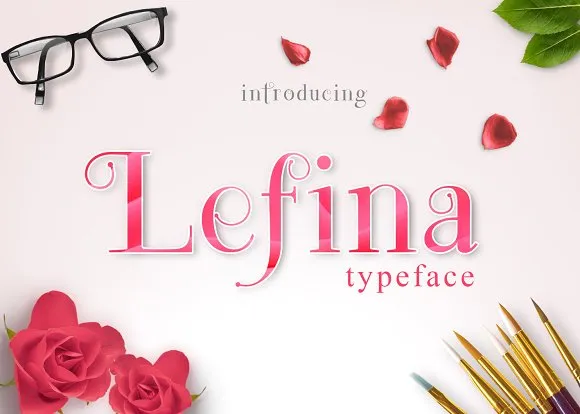
A Lefina Typeface é uma seleção elegante para projetos que exigem destaque visual. Esta tipografia Display se destaca com linhas leves e traços retos, criando um estilo arredondado que contrasta perfeitamente com o seu conteúdo. Foi criada pelo designer Syafrizal, que apresenta uma escolha única para quem busca um design minimalista, mas não menos sofisticado. Para usuários interessados em incorporar a Lefina Typeface em seus trabalhos comerciais, é fácil encontrar a fonte através da página do autor no CreativeFabrica. A Lefina oferece um equilíbrio perfeito entre modernidade e elegância, tornando-a uma ótima opção para qualquer aplicação visual de destaque. Se você tiver dúvidas ou precisar de ajuda com projetos que envolvam essa fonte especial, Syafrizal está sempre disponível para conversar. Lembre-se de enviar seu feedback ou solicitações pelo endereço . Não espere mais e descubra como a Lefina pode transformar seus materiais em um verdadeiro destaque no mundo da comunicação visual.
Designer: Syafrizal